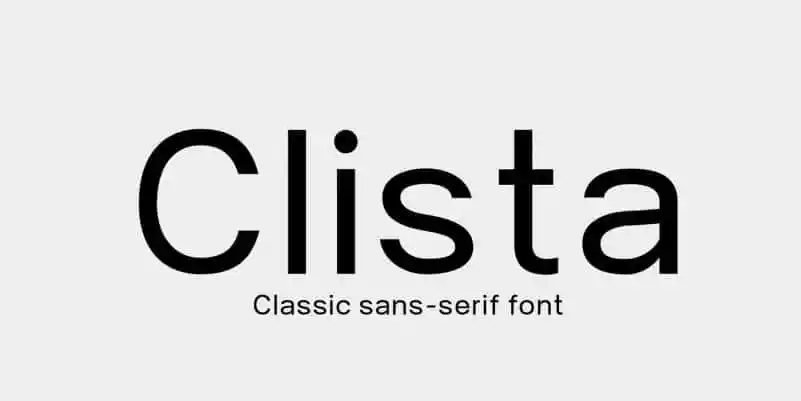
Clista Sans Serif font – Download Grátis
A Clista Sans Serif é uma fonte geométrica sem serif que expressa a simplicidade de forma clara e precisa. Ela foi criada pelo font designer Arief Rochman, pensando no valor estético e em formas geométricas. Perfeita para aplicações gráficas casuais e minimalistas, a Clista oferece uma aparência elegante e moderna que combina perfeitamente com design de conteúdo casual e minimalista. Seja um logo, uma página web ou qualquer outro tipo de design gráfico, esta fonte sem serif traz um toque sofisticado às suas criações, mantendo-se agradável para leitura em qualquer dispositivo. Com sua estrutura geométrica, a Clista Sans Serif é perfeita para arquitetar o aspecto de seu design, seja ela grande ou pequena, a fonte continua sendo uma escolha inteligente e única.